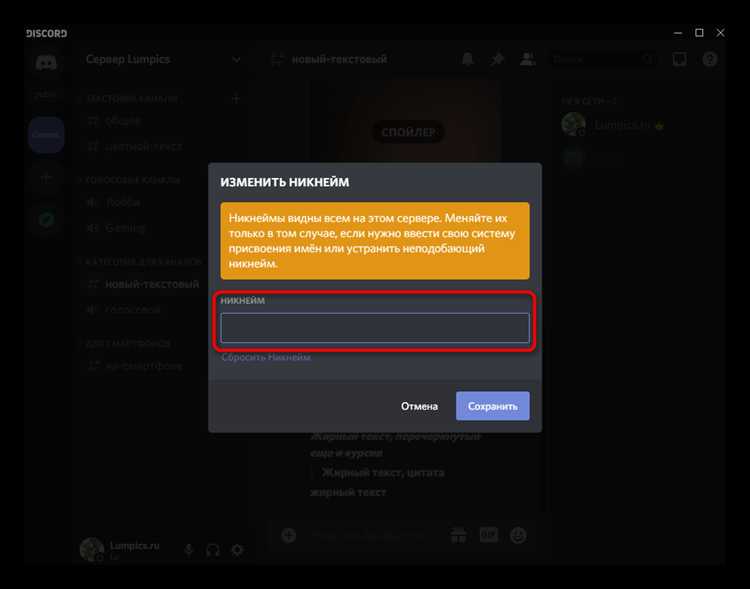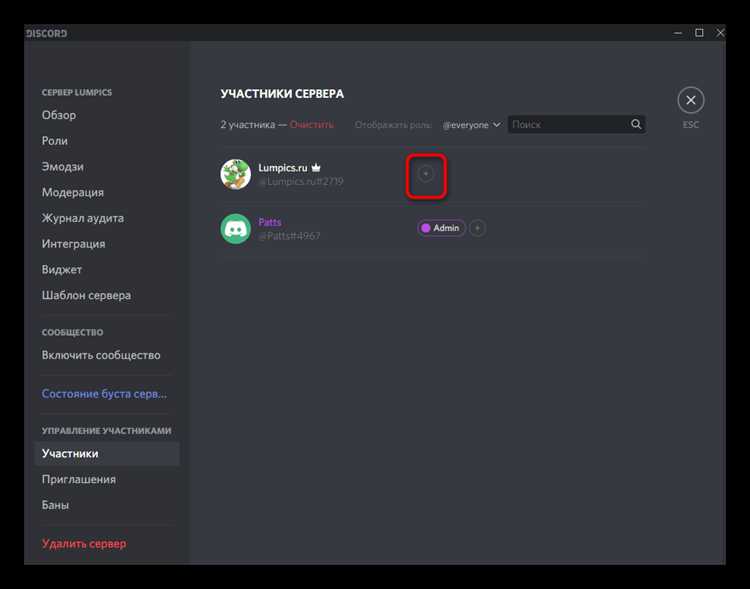
Выбор ника в Дискорде влияет на восприятие вас в сообществах и игровых серверах. Оригинальный ник с уникальным шрифтом помогает выделиться среди тысяч пользователей и запоминается другим участникам. Для достижения этого важно учитывать длину имени, сочетание символов и читаемость на разных устройствах.
Для создания уникального шрифта можно использовать онлайн-генераторы, которые преобразуют стандартный текст в набор символов Unicode, поддерживаемых Discord. Такие инструменты позволяют комбинировать жирные, курсивные и декоративные варианты, а также добавлять специальные знаки и эмодзи, сохраняя совместимость с платформой.
При выборе стиля ника стоит учитывать контекст: игровой сервер, профессиональное сообщество или тематический чат. Слишком сложные или перегруженные символы могут ухудшить читаемость, поэтому рекомендуется тестировать варианты на мобильных и десктопных версиях Discord. Оптимальный ник сочетает креативность с удобством восприятия и поддерживает индивидуальность пользователя.
Выбор подходящего стиля шрифта для ника
При выборе шрифта для ника важно учитывать его читаемость и совместимость с платформой Discord. Стандартные шрифты, такие как Arial или Verdana, обеспечивают максимальную разборчивость, но могут выглядеть обыденно. Для уникальности стоит рассмотреть нестандартные стили: моноширинные, рукописные, декоративные или символические шрифты.
Моноширинные шрифты подходят для минималистичных и строгих ников, создавая аккуратный визуальный эффект. Рукописные шрифты придают никнейму индивидуальность, но длинные имена с такими шрифтами могут быть трудночитаемыми. Декоративные и символические стили добавляют оригинальности, но их стоит использовать умеренно, чтобы не перегружать визуальное восприятие.
При выборе стиля также учитывайте длину ника: короткие имена лучше смотрятся с более выразительными шрифтами, длинные – с простыми и читаемыми. Экспериментируйте с комбинацией символов и букв, чтобы добиться гармоничного внешнего вида, не нарушая разборчивости.
Для окончательного решения полезно протестировать выбранный стиль непосредственно в Discord, оценив, как ник выглядит в разных контекстах: в списке участников, чатах и упоминаниях. Это позволяет выявить сочетания, которые будут одновременно уникальными и удобочитаемыми.
Использование онлайн-генераторов для создания уникального текста
Онлайн-генераторы позволяют быстро преобразовать обычный текст в стилизованный ник для Дискорда. Среди популярных инструментов выделяются «FancyTextGuru», «Lingojam» и «Unicode Text Converter». Они поддерживают множество шрифтов: от рукописных и готических до зеркальных и символических.
Для создания уникального ника достаточно ввести исходное имя в поле генератора и выбрать подходящий стиль. Некоторые генераторы предоставляют возможность комбинировать сразу несколько эффектов, например, добавить символы над и под буквами или использовать чередование верхнего и нижнего регистра.
При выборе генератора стоит учитывать совместимость с Дискордом: не все Unicode-символы корректно отображаются в приложении. Рекомендуется тестировать полученный ник, чтобы избежать обрезки или замены символов при публикации.
Для систематизации вариантов можно использовать таблицу, где фиксируются стиль, символы и итоговый результат. Это помогает выбрать оптимальный вариант без необходимости повторного ввода текста в генератор:
| Стиль | Исходное имя | Результат |
|---|---|---|
| Готический | Owen | 𝔒𝔴𝔢𝔫 |
| Зеркальный | Owen | Инѡ |
| Рукописный | Owen | 𝓞𝔀𝓮𝓷 |
Использование онлайн-генераторов сокращает время на эксперименты с разными шрифтами и позволяет быстро получить визуально привлекательный ник для профиля в Дискорде.
Применение специальных символов и эмодзи в нике
Специальные символы позволяют выделить ник среди других и добавить индивидуальности. Наиболее популярны символы из блоков Unicode, включая стрелки (→, ⇨), декоративные линии (═, ░), математические символы (∑, √) и различные формы (★, ◆). Их сочетание с буквами создает уникальные визуальные эффекты.
Эмодзи расширяют возможности выразительности ника, позволяя передавать настроение или интересы пользователя. Например, 🎮 и 🕹 подходят для игровых аккаунтов, а 🌿 или 🐾 подчеркивают природную тематику. Эмодзи можно размещать в начале, конце или внутри ника для выделения ключевых элементов.
Важно соблюдать баланс: слишком большое количество символов и эмодзи затрудняет чтение имени и может быть некорректно отображено на разных устройствах. Оптимально использовать не более 2–4 эмодзи и 3–5 специальных символов в сочетании с основным текстом ника.
При выборе символов следует проверять совместимость с Discord. Некоторые редкие символы могут не поддерживаться, приводя к их замене на стандартные знаки. Для проверки достаточно вставить символ в поле ника и убедиться, что он отображается корректно в списке пользователей и сообщениях.
Комбинация букв, специальных символов и эмодзи позволяет создать запоминающийся и уникальный ник, который отражает индивидуальность пользователя и подходит под выбранную тематику.
Какие символы и эмодзи лучше использовать для украшения ника?
Подходят простые и легко распознаваемые символы, такие как стрелки, звездочки или минималистичные линии. Эмодзи можно использовать для акцентов, но не стоит перегружать ник. Главное — сохранить читаемость и не нарушить баланс между визуальной привлекательностью и удобством восприятия имени другими пользователями.